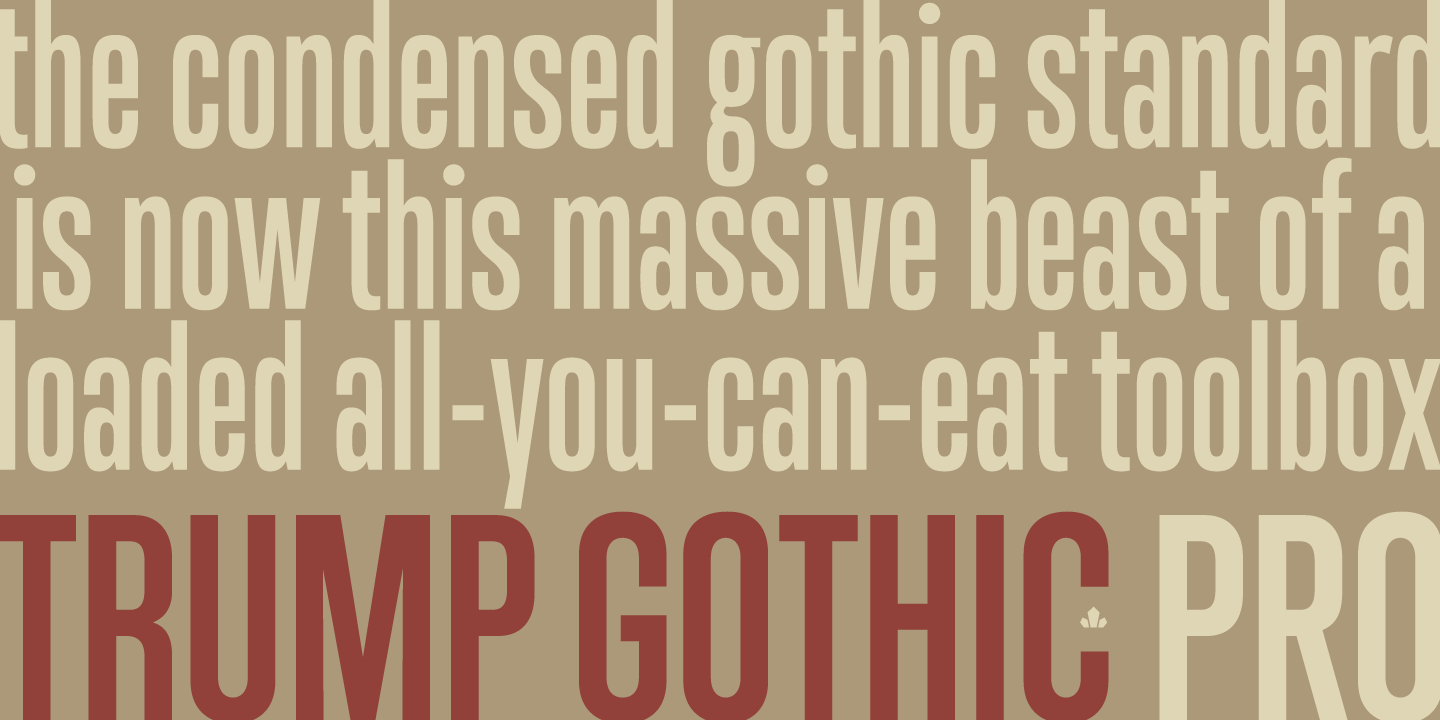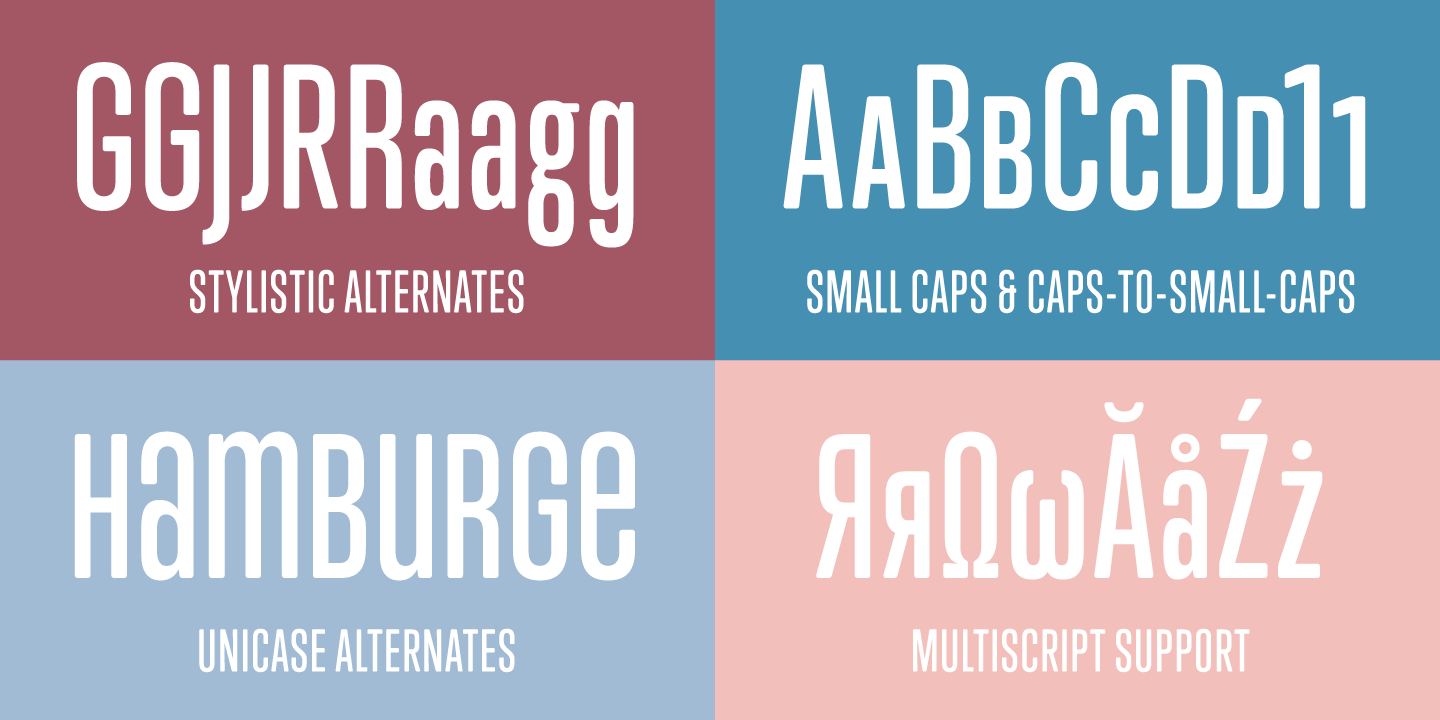
Die Signum ist eine schmale Grotesk von Georg Trump, die 1955 in nur einem Schrift bei C. E. Weber in Stuttgart erschien. Das g ist in zwei Varianten verfügbar (siehe Abbildung unten).
Eine umfangreich ausgebaute Neubearbeitung gibt es von Canada Type. Die Trump Gothic Pro verfügt über drei Strichstärken mit Kursiven und einer lateinischen, kyrillischen und griechischen Zeichenbelegung. Außerdem gibt es die Trump Soft Pro mit abgerundeten Ecken. Beide Familien verfügen auch über Kapitälchen.
Figurenverzeichnis der Bleisatzversion
Trump Gothic von Canada Type